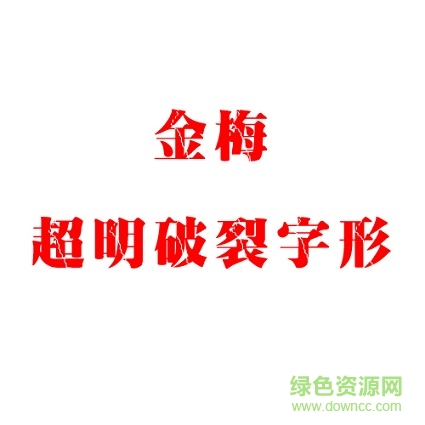
軟件介紹 軟件標(biāo)簽: 金梅 破裂字體 字體 金梅超明破裂字形又稱金梅超明裂痕字體。該字體最大的特點在于,破裂效果非常明顯,更能彰顯裂痕體的字形效果,對于設(shè)計師們來說,應(yīng)該經(jīng)常會用到。字體安裝方法WIN7系統(tǒng)直接雙擊TTF文件進行安裝即可;XP系統(tǒng)將TTF文件復(fù)制C:\Windows\Fonts文件夾即可 軟件截圖 上一張下一張(1 / 1) 安裝詳細截圖 猜你喜歡 金梅字體 裂痕字體 金梅字體 金梅字體是以繁體字形為主,多數(shù)的金梅字體都是繁體。金梅字體給人的感覺比較多樣,有的比較圓潤,有的比較可愛,還有破裂的字體,于楷體形成了鮮明的對比,沒有固定的樣式。金梅字體多用于廣告制作、海報制作、封面制作等。 查看更多>> winman tun10011字體 17.57M/中文/6.6/下載 金梅浪漫原體國際碼 1.91M/中文/6.6/下載 金梅粗明原體國際碼 1.41M/中文/5.0/下載 金梅流行書 2.78M/中文/10.0/下載 金梅綜藝菱心 4.19M/中文/10.0/下載 金梅浪漫小胖 3.44M/中文/10.0/下載 裂痕字體 裂痕字體又叫破裂字體,簡單的來說就是將文字加上裂痕,做成破裂或撕裂效果。霹靂字體其實也屬于裂痕字體,只是給文字加上閃電劃破的效果,實際效果跟裂痕字體差不多。裂痕字體會給人一種撕心裂肺,或者說是破碎,傷心的感覺。 查看更多>> 金梅特黑裂開體字體 2.25M/中文/3.4/下載 金梅顏楷破裂字形 3.87M/中文/10.0/TTF格式下載 金梅超黑破裂字體 2.40M/中文/5.0/下載 金梅超明破裂字形 3.61M/中文/3.3/TTF版下載 金梅顏楷破裂字形(繁) 3.87M/繁體/10.0/下載 金梅毛行破裂字形(繁) 3.71M/中文/10.0/TTF版下載 其他版本下載 標(biāo)題 大小 更新日期 下載 下載地址 電腦版 金梅超明破裂字形 TTF版 點擊報錯 軟件無法下載或下載后無法使用,請點擊報錯,謝謝! 關(guān)閉報錯反饋 請描述您所遇到的錯誤,我們將盡快予以修正,謝謝! *必填項,請輸入內(nèi)容 本類最新 金梅海報美工體 金梅新箭頭字范例字體 免費版 金梅特黑水花字形字體 免費版 金梅粗尖頭字范例繁體字體 免費版 金梅淡古字ttf 免費版 金梅浪漫鏡射體 相關(guān)文章 Photoshop字體安裝使用方法和技巧 如何解決“無法新增字體”問題 Win 7系統(tǒng)安裝字體方法 網(wǎng)頁字體大小設(shè)置方法 怎么改網(wǎng)頁字體大小 在Linux系統(tǒng)中安裝字體的幾種方法 windows7字體顯示問題:打開某些程序的時候顯示的是亂碼 用戶評論 熱門評論 最新評論 發(fā)表評論 查看所有評論(0) 昵稱: 請不要評論無意義或臟話,我們所有評論會有人工審核. 字數(shù): 0/500 (您的評論需要經(jīng)過審核才能顯示)